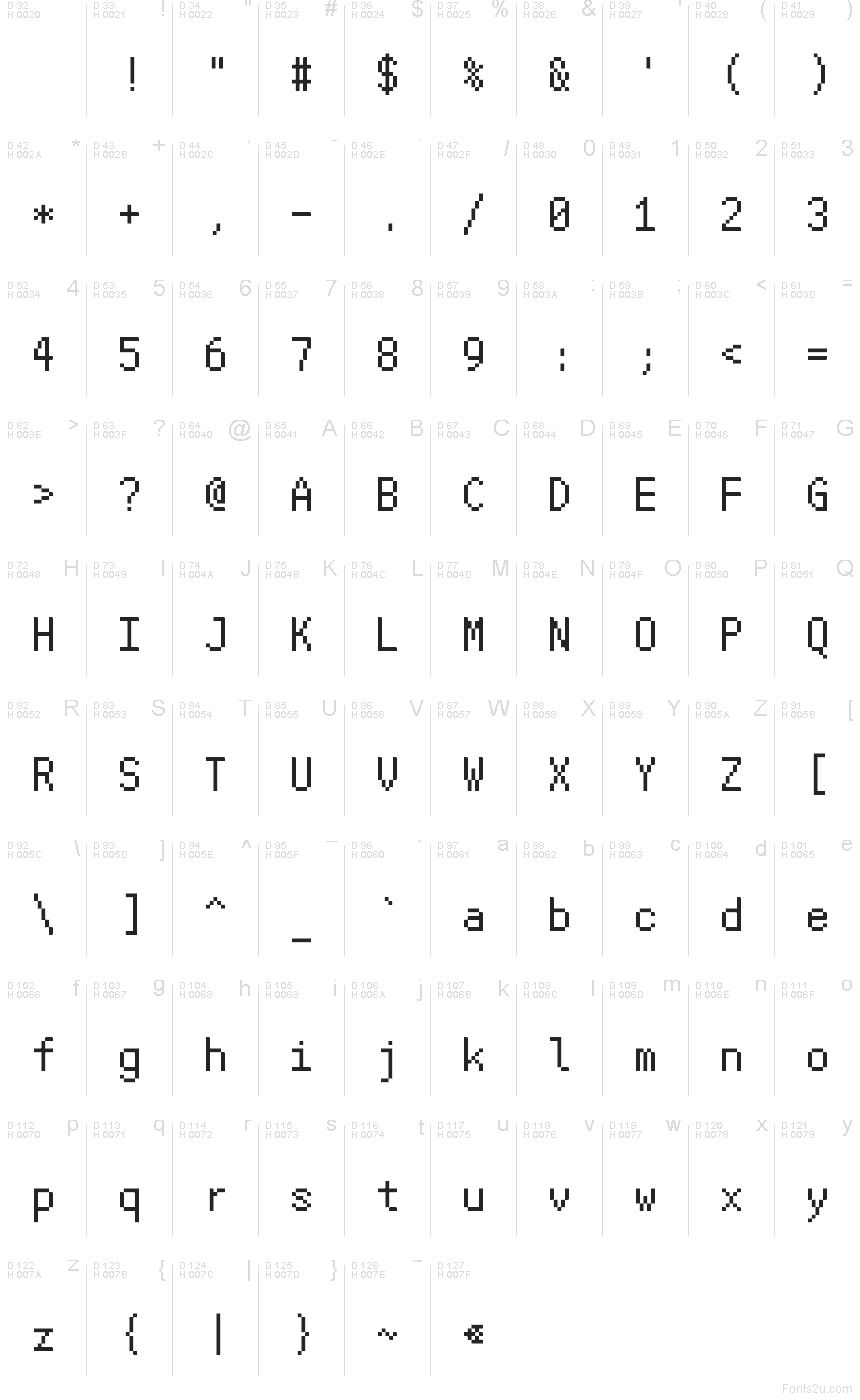
FS 126 Sans é uma fonte bitmap de pixel gratuita da Houlaiziaa, com letras construídas a partir de uma grade quadrada rigorosa e uma atitude direta, típica dos primeiros ecrãs. As formas parecem mais despojadas e levemente peculiares do que puramente mecânicas, com diagonais em degraus e curvas cortadas que conferem à fonte um ritmo digital seco.
Encaixa-se naturalmente em menus de jogos, gráficos de apps retro, títulos de cartazes, zines e etiquetas de interface curtas onde esse ritmo quadrado é o ponto alto. Como é uma fonte gratuita, também funciona bem para linhas de capa, cartões de título e experiências com logótipos compactos, especialmente quando quer que as letras pareçam codificadas, modulares e com um toque lo-fi.